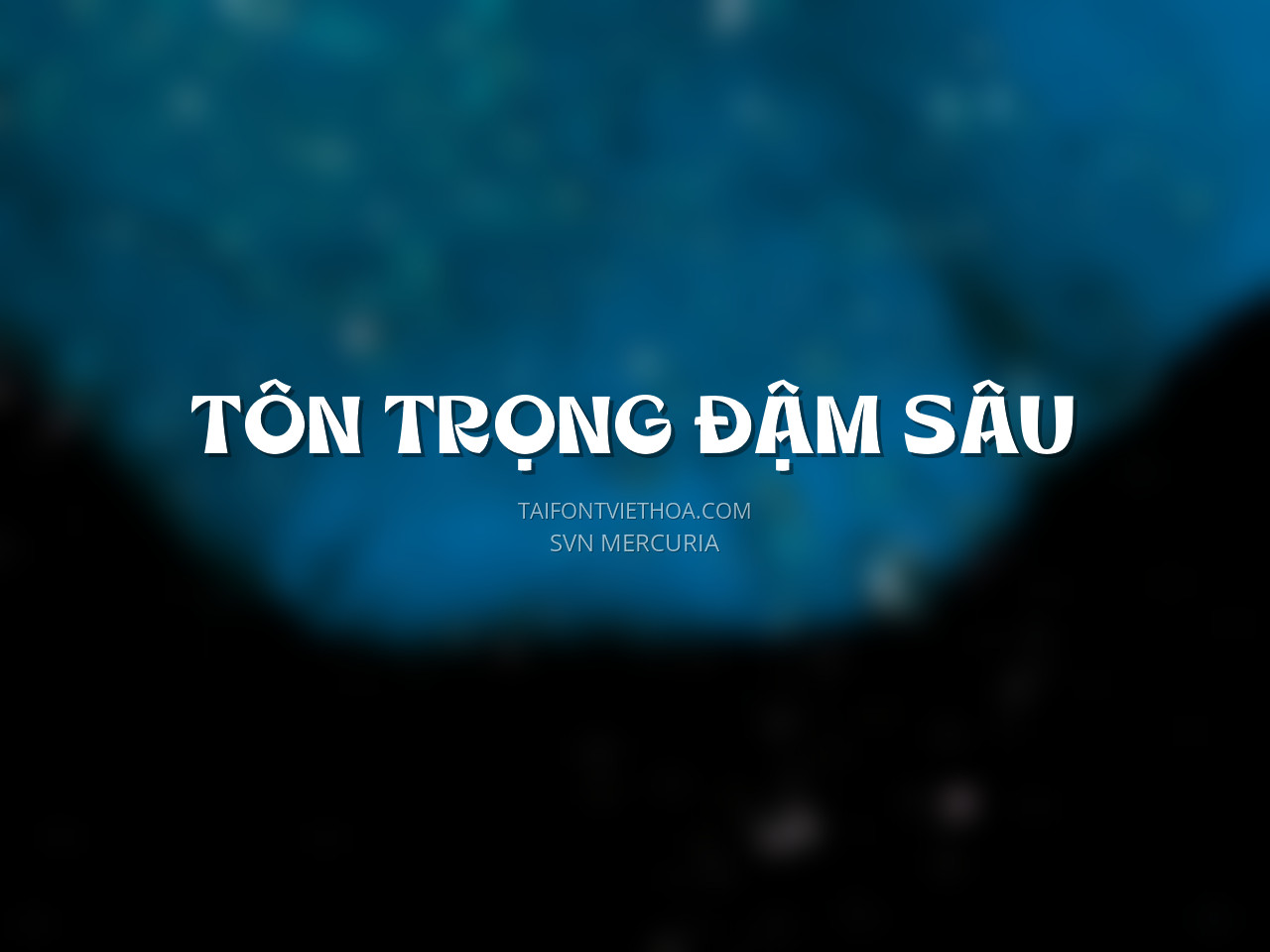
Font việt hóa SVN Mercuria
Tác giả Font: Franco Fuentes
Giới thiệu về font SVN Mercuria – Kiểu chữ serif thanh lịch, mạnh mẽ và hiện đại
SVN Mercuria là phiên bản Việt hóa của font Mercuria – một kiểu chữ serif với thiết kế tinh tế, sắc nét và đầy cá tính. Font kết hợp giữa phong cách cổ điển và hiện đại, mang lại sự cân đối và dễ đọc, rất phù hợp cho các dự án thiết kế thương hiệu, ấn phẩm cao cấp và truyền thông chuyên nghiệp.
Phiên bản Việt hóa của SVN Mercuria được Taifontviethoa.comhoàn thiện kỹ lưỡng, hỗ trợ đầy đủ dấu tiếng Việt cùng hơn 80 ngôn ngữ khác. Font giúp nhà thiết kế dễ dàng ứng dụng trong nhiều lĩnh vực đa dạng, từ in ấn đến kỹ thuật số, đồng thời giữ được vẻ đẹp thanh lịch và chuyên nghiệp.
Thiết kế serif sắc nét – Ứng dụng rộng rãi trong thương hiệu và xuất bản
SVN Mercuria sở hữu cấu trúc serif với các nét chữ sắc sảo, độ tương phản cao và các chi tiết tinh tế ở chân chữ và đầu nét. Font phù hợp sử dụng cho đoạn văn bản dài và tiêu đề, giúp tăng tính thẩm mỹ và sự chuyên nghiệp cho thiết kế. Phong cách của Mercuria mang đến sự trang nhã và đẳng cấp cho mọi sản phẩm sử dụng.
Ứng dụng lý tưởng: thiết kế nhận diện thương hiệu, bìa sách, tạp chí, brochure, thư mời, danh thiếp và các ấn phẩm quảng cáo cao cấp. Ngành nghề phù hợp: thời trang, mỹ phẩm, nội thất, nghệ thuật, xuất bản và các thương hiệu định vị theo phong cách sang trọng, chuyên nghiệp.